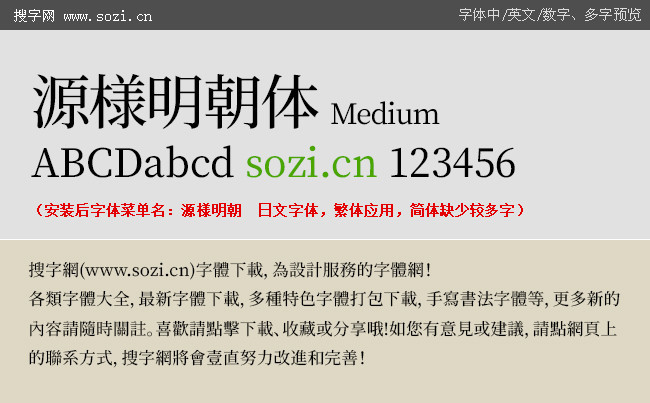
源様明朝Medium
搜字網(wǎng)給大家提供一款源様明朝Medium文字體下載,源様明朝體源自思源宋體,源樣明體采用思源宋體韓文版本的字符,配合繁體中文習(xí)慣的置中標(biāo)點符號,可說是兼具排版及傳統(tǒng)印刷體風(fēng)格的繁體中文字體。適用于大標(biāo)題、包裝設(shè)計、海報設(shè)計等應(yīng)用。